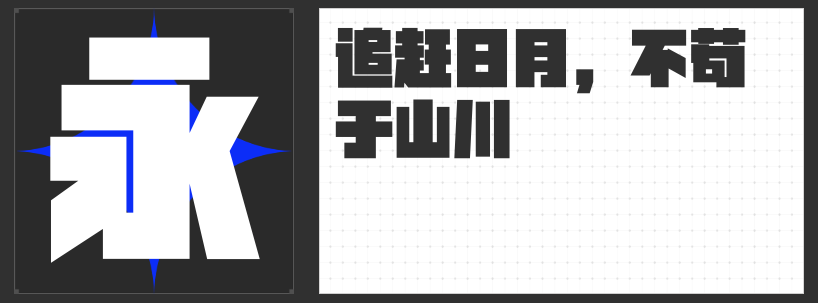
四款创意字体推荐:以独特笔触重构视觉语言
在平面设计的多元表达中,创意字体如同视觉符号的“语言重构者”,通过突破常规的笔画形态与结构逻辑,为作品注入鲜明的个性与情感张力。以下四款字体以独特的创意基因,在传统与现代、理性与感性的碰撞中,开辟出别具一格的美学路径。
一、造字侠朝凤宋简
这款宋体以宽扁形态重构经典比例,横画起笔的圆角与收笔的方折形成微妙对话,撇捺的流畅曲线与切笔收尾的几何凸起碰撞出力量与柔美的双重韵律。点画以半圆切笔收尾,钩画外圆内方,在布白均匀的框架中,通过几何化处理将传统宋体的书卷气转化为现代设计语言,既保留文化底蕴,又具备强烈的视觉冲击力。
二、造字侠磅礴简繁
灵感源自书法运笔的“一波三折”,这款字体通过粗细对比强烈的笔画与飞白效果,模拟出书写时的力度变化。转折处方圆交融,中宫开阔的布局赋予字形呼吸感,在保留手写温度的同时,以数字化精度重构书法美学。其动态的笔画节奏,尤其适合需要传递文化厚度与情感张力的设计场景。
三、励字开拓者简 超特黑
以直线与几何切割为核心,这款超特黑字体通过横平竖直的笔画、平切起收笔与均匀的内部空间,构建出理性而秩序感极强的视觉体系。去钩化处理与竖直撇捺点设计,强化了字形的镜像对称性,在简约中暗藏视觉陷阱,为科技、工业主题设计提供冷静而锐利的表达载体。
四、高手字斋哥特体Pro
哥特式尖拱与重金属质感的融合,赋予这款字体阴森庄重的仪式感。锐利的装饰性衬线与粗壮的笔画主干形成压迫性对比,在可变字宽的调节下,既能呈现狭窄空间中的尖锐张力,亦可延展为宽幅排版中的肃穆气场,为影视、游戏等需要沉浸式氛围的场景提供视觉锚点。
这四款字体通过解构传统、融合多元文化符号,以创意笔触重新定义了字形的表达边界。无论是几何宋体的东方美学、书法韵律的数字化重生、极简主义的理性实验,还是暗黑美学的戏剧化演绎,均以独特的设计逻辑为设计师提供了突破常规的创意工具。